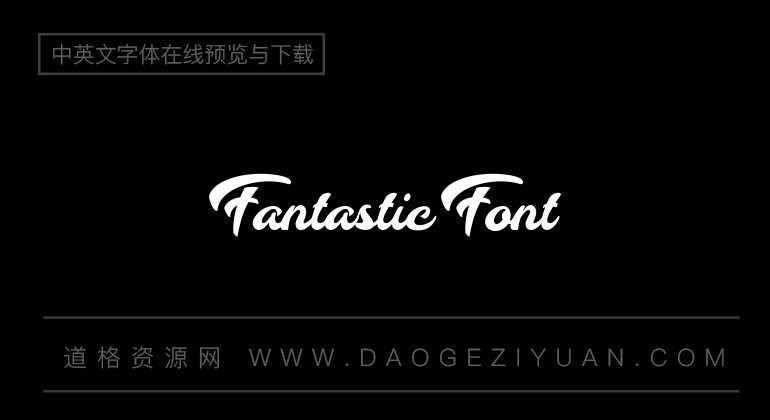
Fantastic Font 是一种创意的字体,具有非常独特和有趣的外观。它的设计灵感来自于漫画、游戏和科幻电影等文化元素。这种字体的形状充满了怪异、充满幻想的元素,它可以在设计、标志、海报等领域中被用于吸引观众的目光。由于这种字体具有很高的辨识度和独特性,它经常被用于表示创新、未来和前沿的意象。Fantastic Font 适合用于数字艺术、科幻小说、漫画书、游戏界面、影视动画等领域,是一种充满想象力和创造力的设计工具。内容介绍
Fantastic Font是一款非常不错的手写艺术字体,具有很好的视觉感,适合于文化类的宣传设计、商业类品牌的广告和产品包装设计以及个性化文字排版等较多场景。